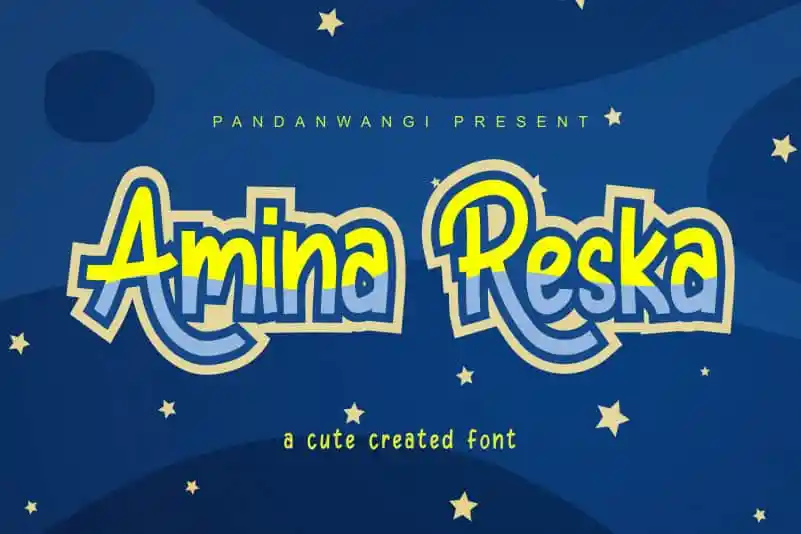
Amina Reska Font – Fonte Grátis
Amina Reska Font
A fonte Amina Reska é uma escolha ideal para quem busca um toque divertido e criativo no seu design visual. Desenvolvida com paleta de cores vibrantes e um estilo descontraído, essa fonte atinge diretamente o coração dos criativos que desejam dar um twist leve em suas criações. Perfeita tanto para arquitetos de casamento buscando um toque pessoal em sua cartilha, como para designers de revistas querendo deixar seus posts sociais mais atraentes, ou até mesmo para quem deseja criar cards de aniversário com uma cara descontraída. Com o Amina Reska Font, cada trabalho criativo recebe um brilho extra e ganha destaque instantâneo. Este é um verdadeiro companheiro de criação que abraça as ideias mais ousadas e inusitadas, sempre prontos para acompanhar suas aventuras no mundo da design gráfica. Não há limites para o que você pode criar com essa fonte, a não ser pelos próprios desejos!